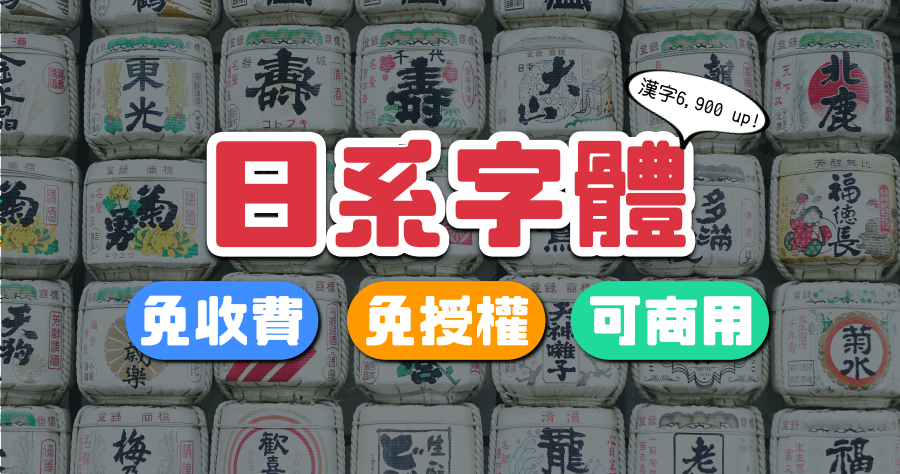
よく飛ばない鳥可商用免費字體下載,讓你遠離字體侵權之亂!
△ 我們先點擊「黃色」的按鈕,來到「 Quiz 」這個主題的字型,其實 Quiz 指的是日本的「猜謎節目」畫面中,做效果的字體。猜謎節目是什麼呢?在櫻桃小丸子動畫卡通中有出現過喔:爺爺參加猜謎節目 上集。總之我們可以看到「 Quiz 」這個字型又有戲分很多種,如下方藍色字的部分。
接下來讓  9m87 我替大家試用幾個字體,都是滿好看的,推薦給大家:
△ チェックポイントフォント,約 6,900 個漢字:
△ チェックアンド横断フォント,約 6,900 個漢字:
△ チェックポイント★リベンジ,約 1,026 個漢字:
△ ぎゃーてーるみねっせんす,約 6,900 個漢字:
△ きずだらけのぎゃーてー,約 6,900 個漢字:
以上就是我替大家整理的五個免費可商用日系字體,是不是非常有特色呢?我最喜歡的就是手寫字體,也就是上面我用魏瓔珞以及富察傅恆做範例的那兩個,風格樸實又可愛~由於這個網站很明確的說明可以自由運用這些字體在網頁、印刷品或是影片中,因此大家可以放心地使用,在創作時省去煩惱字體侵權的疑慮,好好的去創作吧!